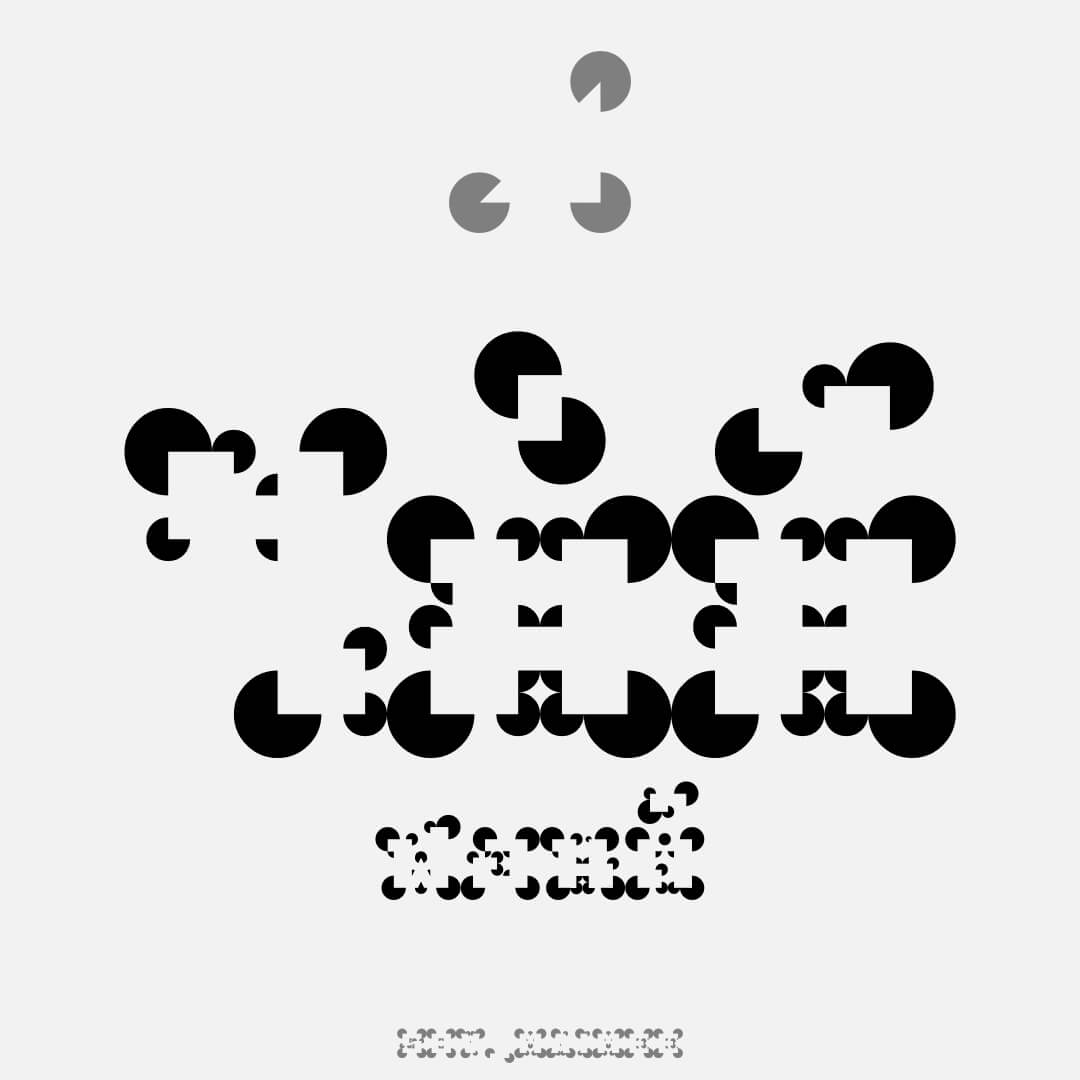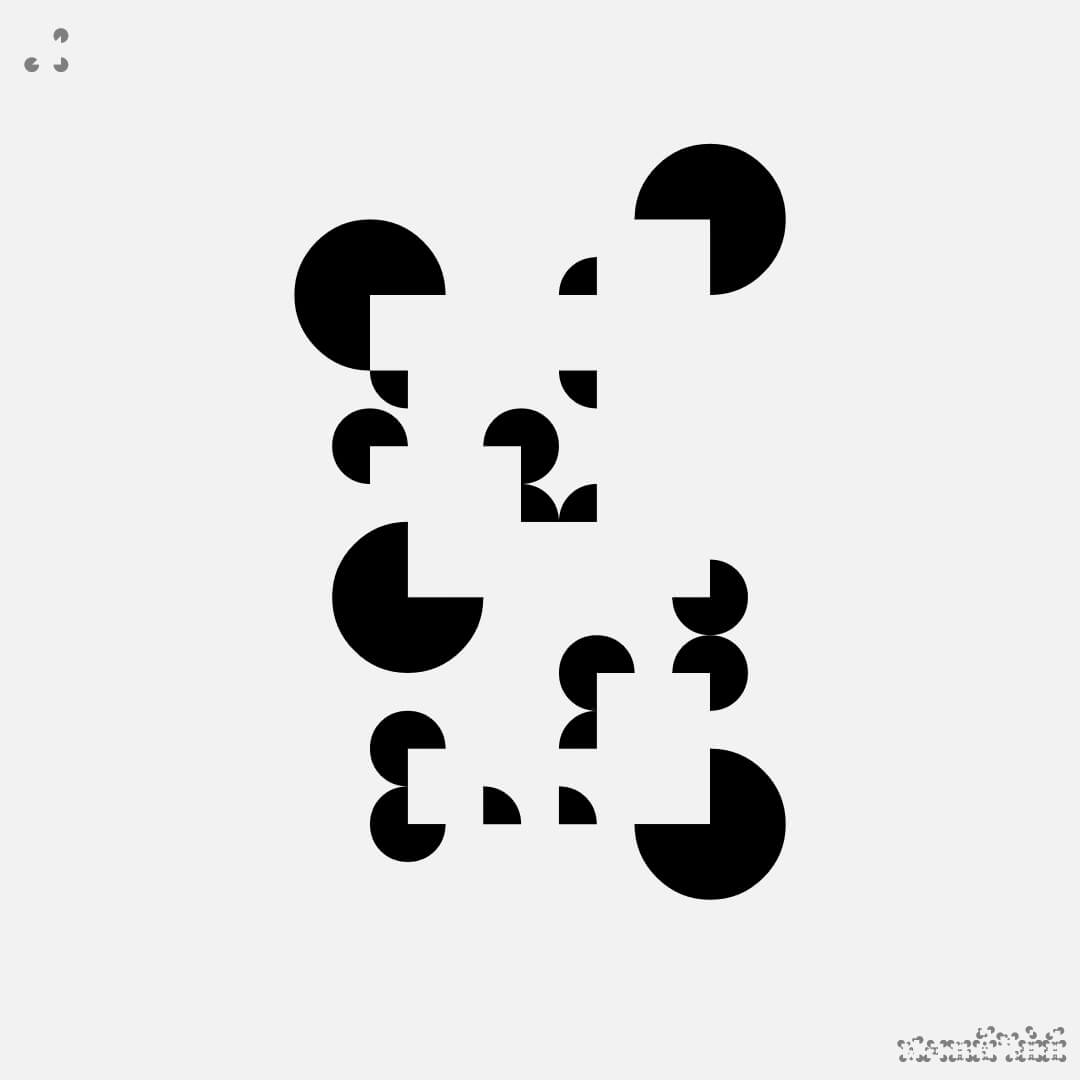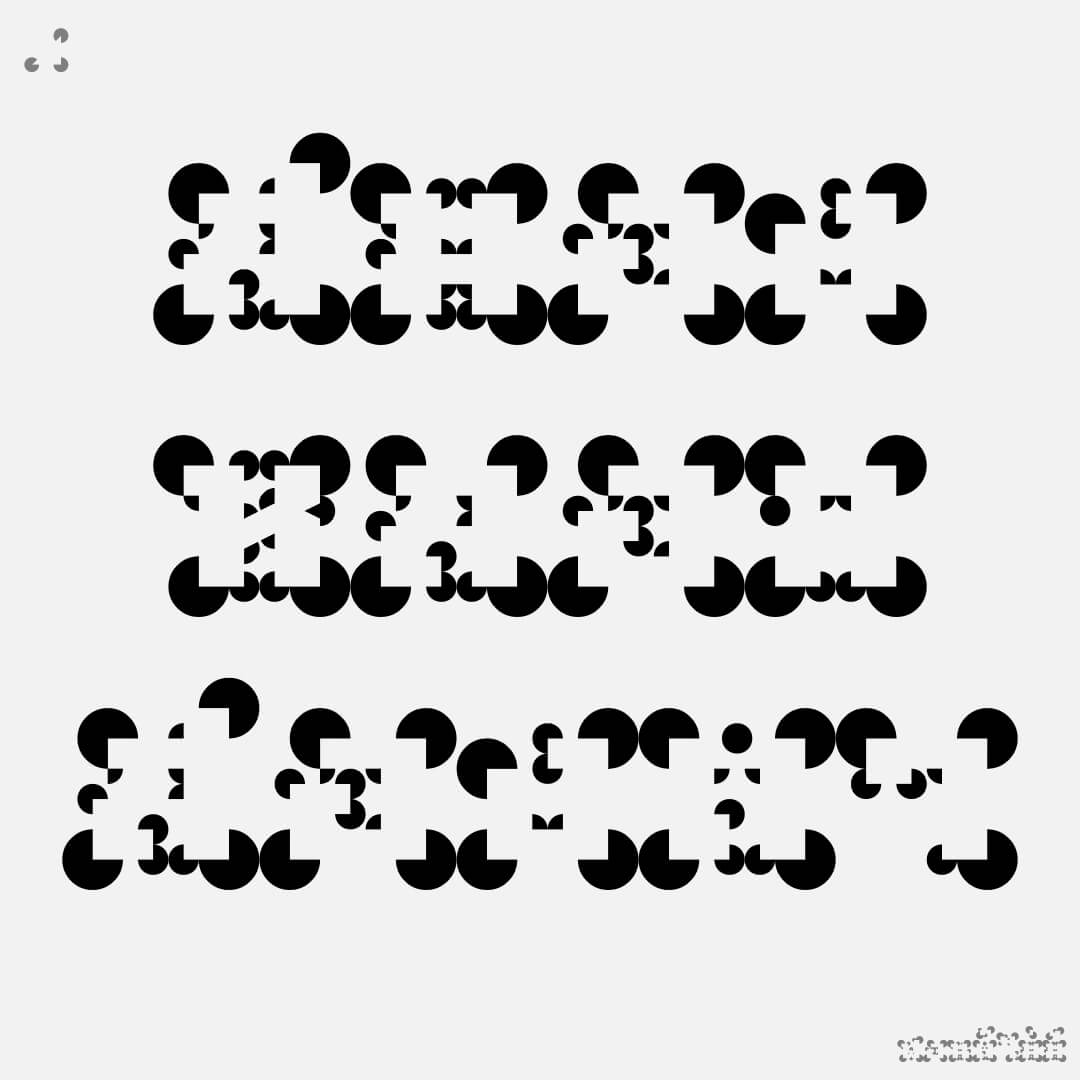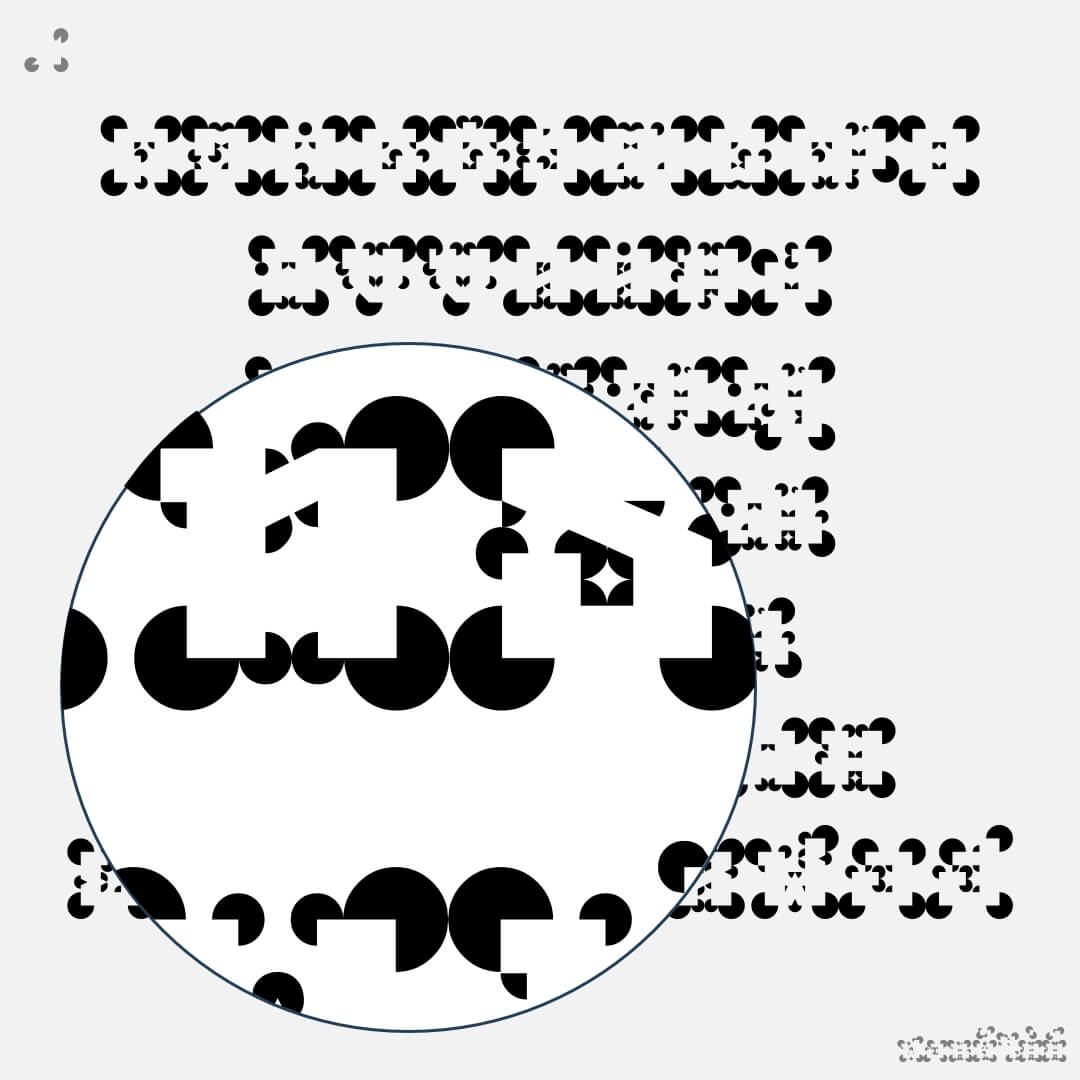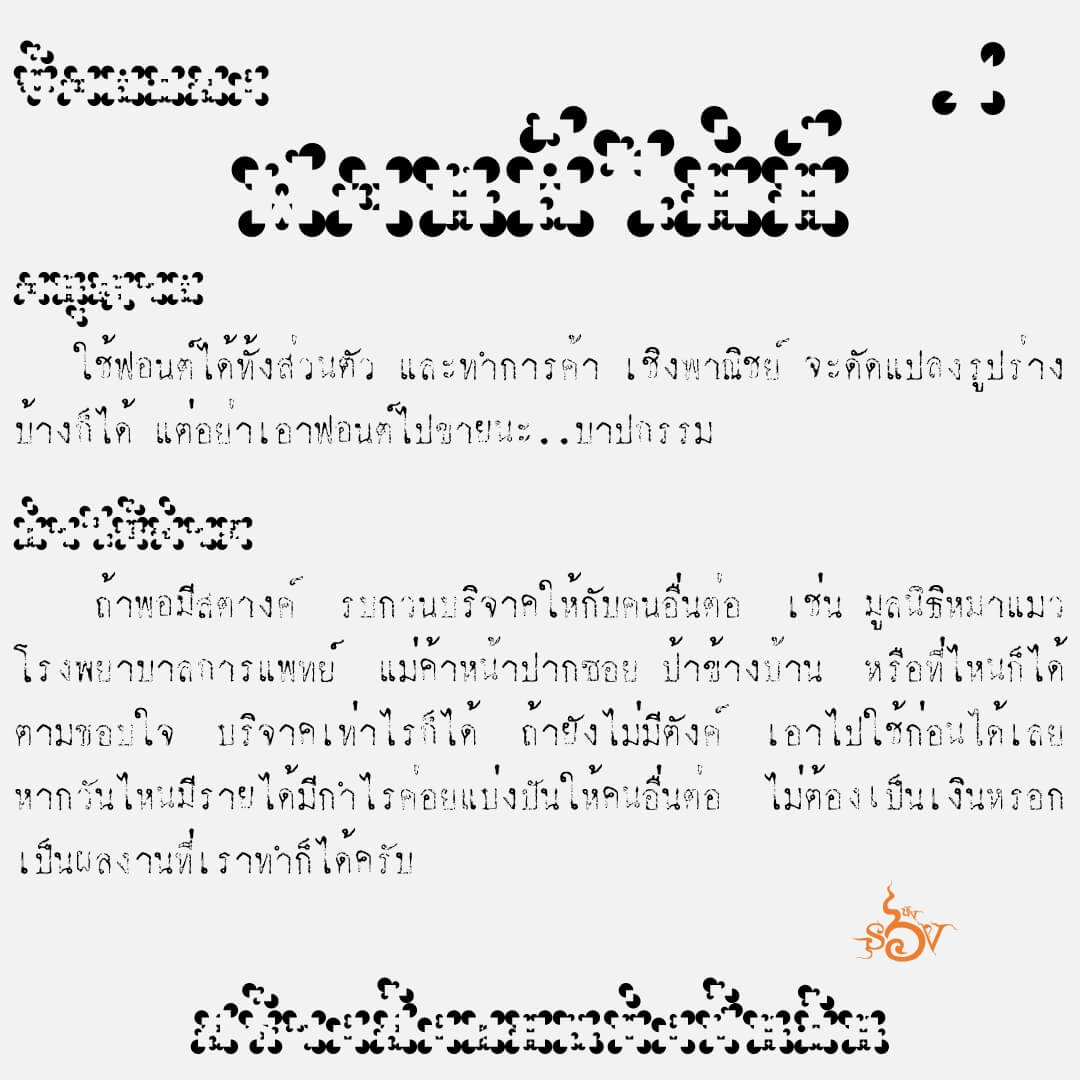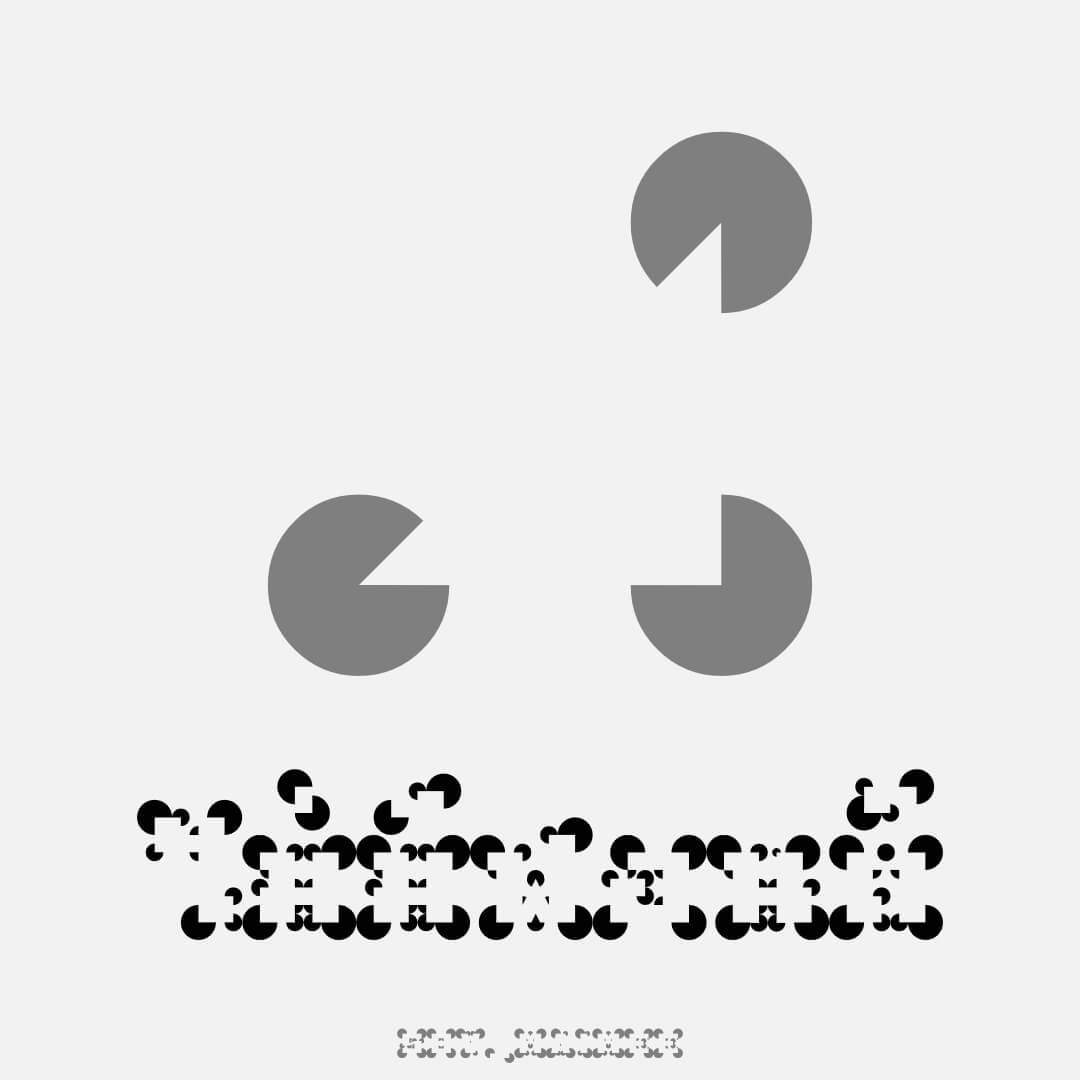
ฟอนต์ไม่มี – ไม่มีฟอนต์ ไม่ลากเส้นตัวอักษร มีแต่รูปวงกลมและรอยแหว่ง ที่เหลือเป็นเรื่องของตาและสมองที่หลอกกันเอง… ถ้าจะใช้งานต้องเป็นอักษรขนาดใหญ่มากๆ เท่าน้านนนนน
เบื้องหลังการออกแบบ : ฟอนต์ ไม่มี
ไม่มี (SOV_Maimee)